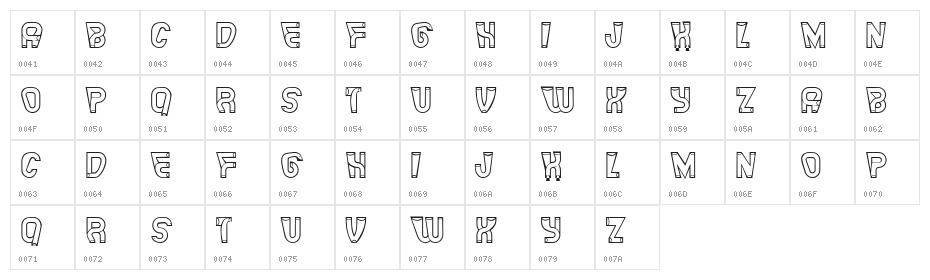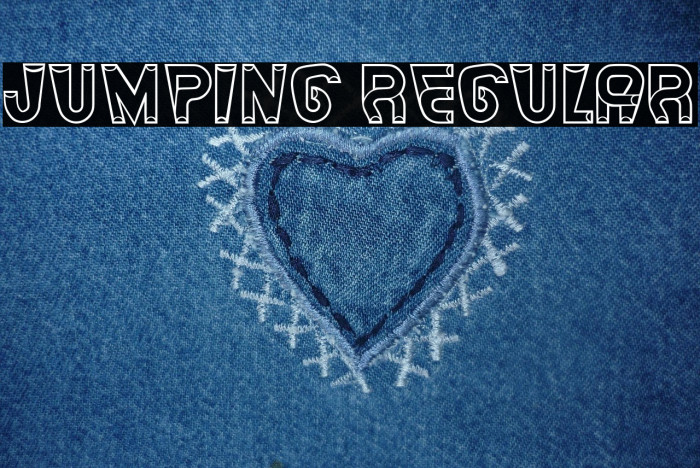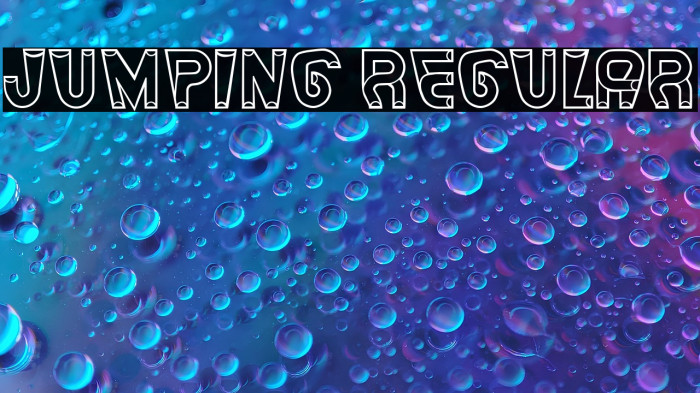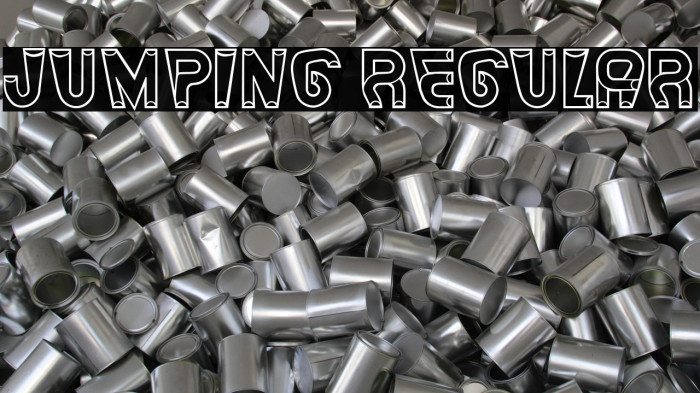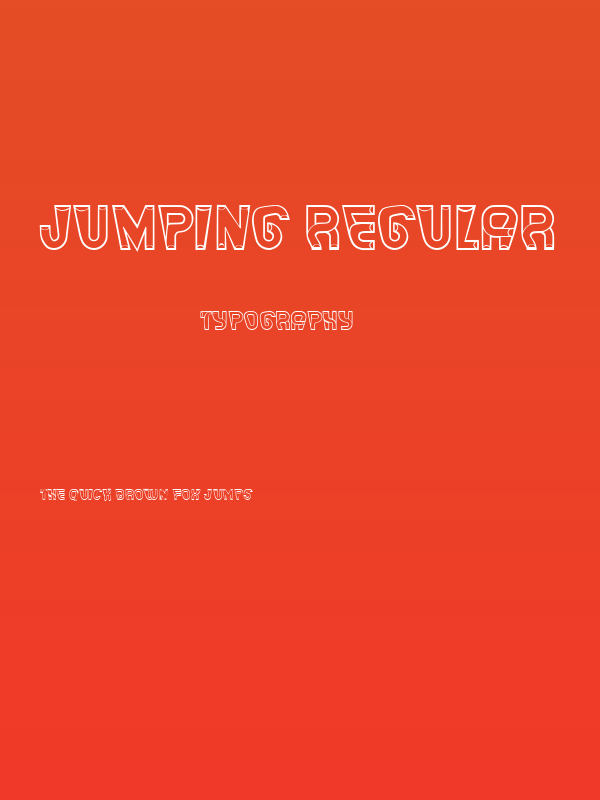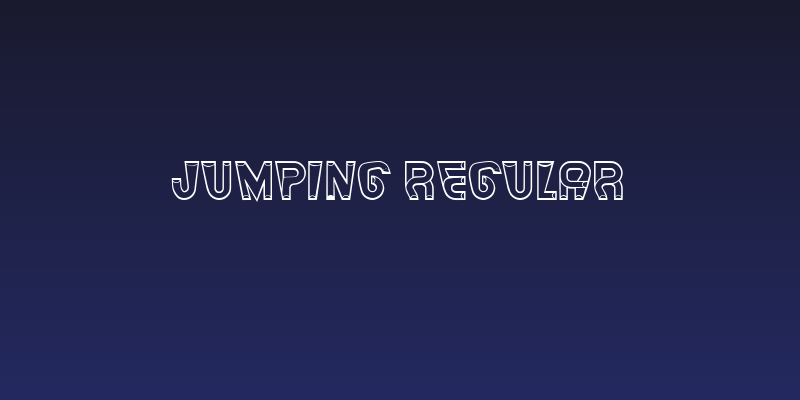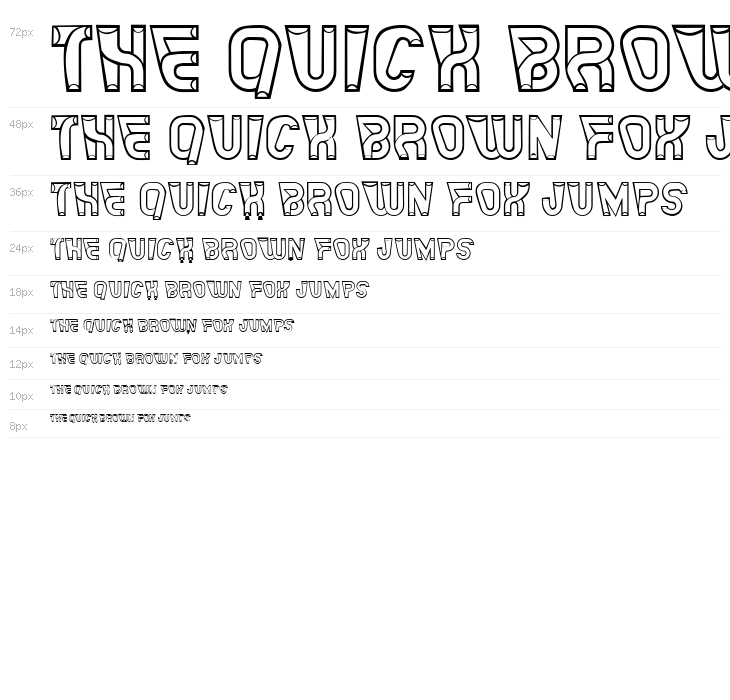
Jumping Regular Font
| Proyectos propuestos | Ideal for posters, event flyers, children's book covers, and any design requiring a fun and energetic typeface. |